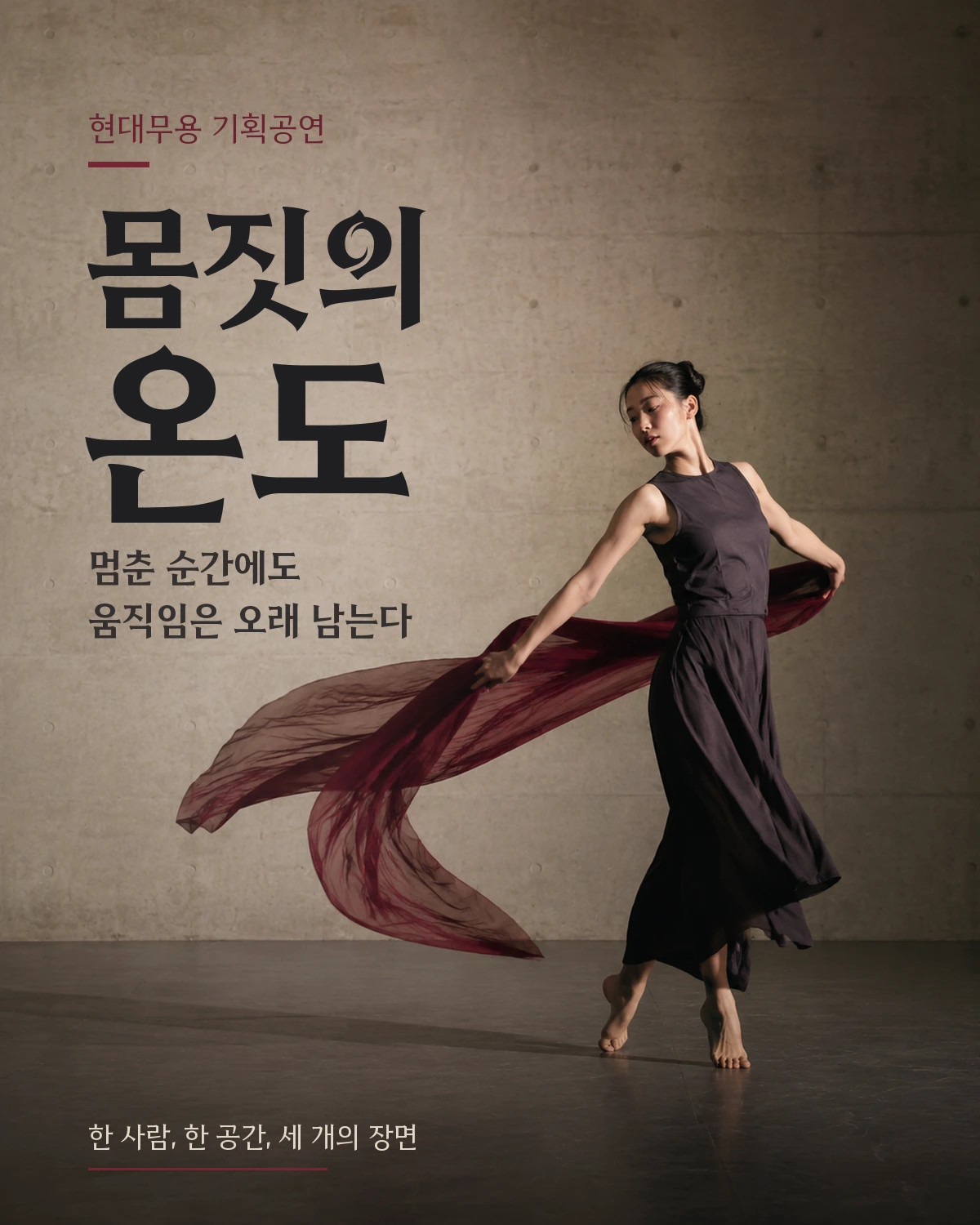
던파 연단된 칼날 — (주)네오플에서 배포하는 무료 폰트입니다. 거침없이 돌아가는 톱니바퀴의 잔상을 조형에 담아, 강한 의지를 벼려 낸 제목용 서체
네오플이 던전앤파이터를 위해 만든 전용 서체로 윤디자인이 제작했습니다. 모티브가 분명합니다. 제작사는 거침없이 돌아가는 톱니바퀴를 모티브로 삼아 운명의 굴레 속에서 연단된 칼날의 강한 저항력과 의지를 담았다고 밝혔습니다.
디자이너는 톱니바퀴를 그대로 그려 넣는 대신 회전의 잔상을 조형의 답으로 삼았다고 인터뷰에서 밝혔습니다. 자소마다 톱니 모양을 넣기보다 글자 전체의 인상으로 그 이미지를 가져가려 했다는 것입니다. 여기에 뾰족한 세리프를 더해 게임 특유의 타격감과 액션감을 냈습니다. 이름은 고딕처럼 들리지만 실제로는 부리가 있는 세리프 계열입니다.
굵기는 Light와 Medium, Bold 세 가지이고 현대 한글 11,172자를 모두 담았습니다. 무료로 쓰고 배포할 수 있지만 임의로 수정하거나 편집할 수 없고 배포된 형태 그대로 써야 합니다. BI나 CI로 쓸 수 있는지는 안내처마다 표기가 달라, 로고에 쓰실 계획이라면 네오플에 확인하시는 편이 안전합니다.